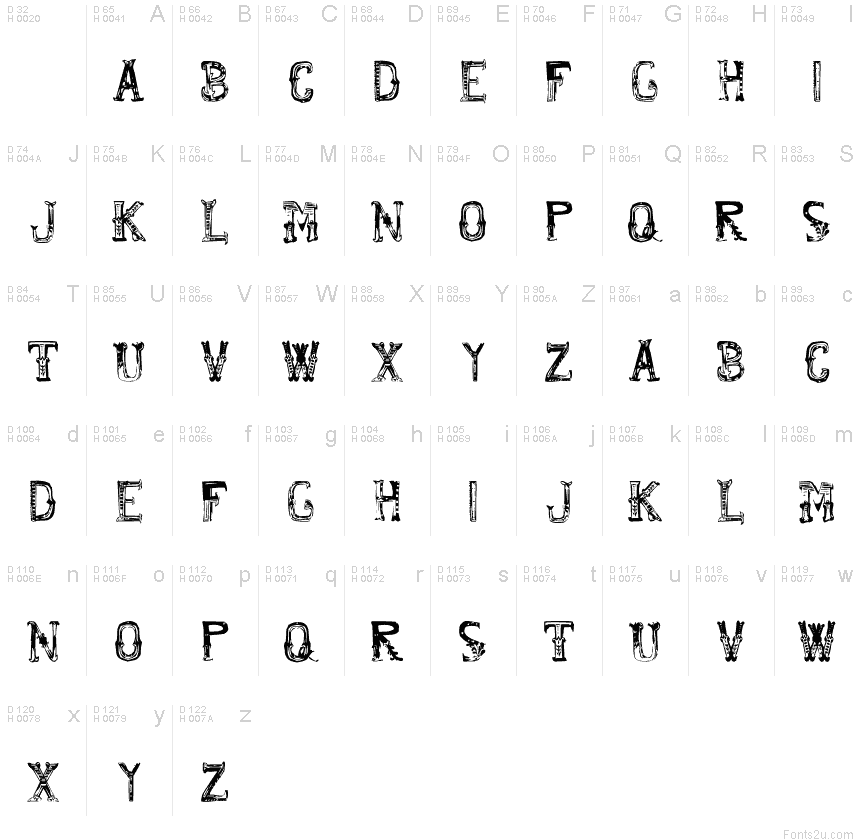
Francis Mirtha هو خط عرض (display) مجاني بنمط رعب يتميز بطابع مرسوم يدوياً يبدو كأنه متحلل. تبدو الحروف وكأنها مخالب، ممزقة، ومغطاة قليلاً بالنباتات؛ حيث يمزج الخط بين القصات التي تبدو وكأنها تقطر وبين الزخارف الشوكية الشبيهة بالنباتات، مما يضفي على الحروف الكبيرة لمسة من القصص الخيالية المظلمة بدلاً من الأسلوب القوطي التقليدي.
يصلح هذا الخط للملصقات، وأغلفة الكتب، وتصاميم الهالوين، وبطاقات العناوين، ورسومات المنتجات (merch) القصيرة حيث يمكن للخط أن يحدد الأجواء بمفرده. وبما أنه خط مجاني، فهو مناسب أيضاً للعناوين الجذابة على وسائل التواصل الاجتماعي أو للحروف الاستهلالية (drop caps)، لأن حوافه غير المنتظمة وتفاصيله الزاحفة تمنحك تأثيراً قوياً حتى في الكلمات القصيرة.